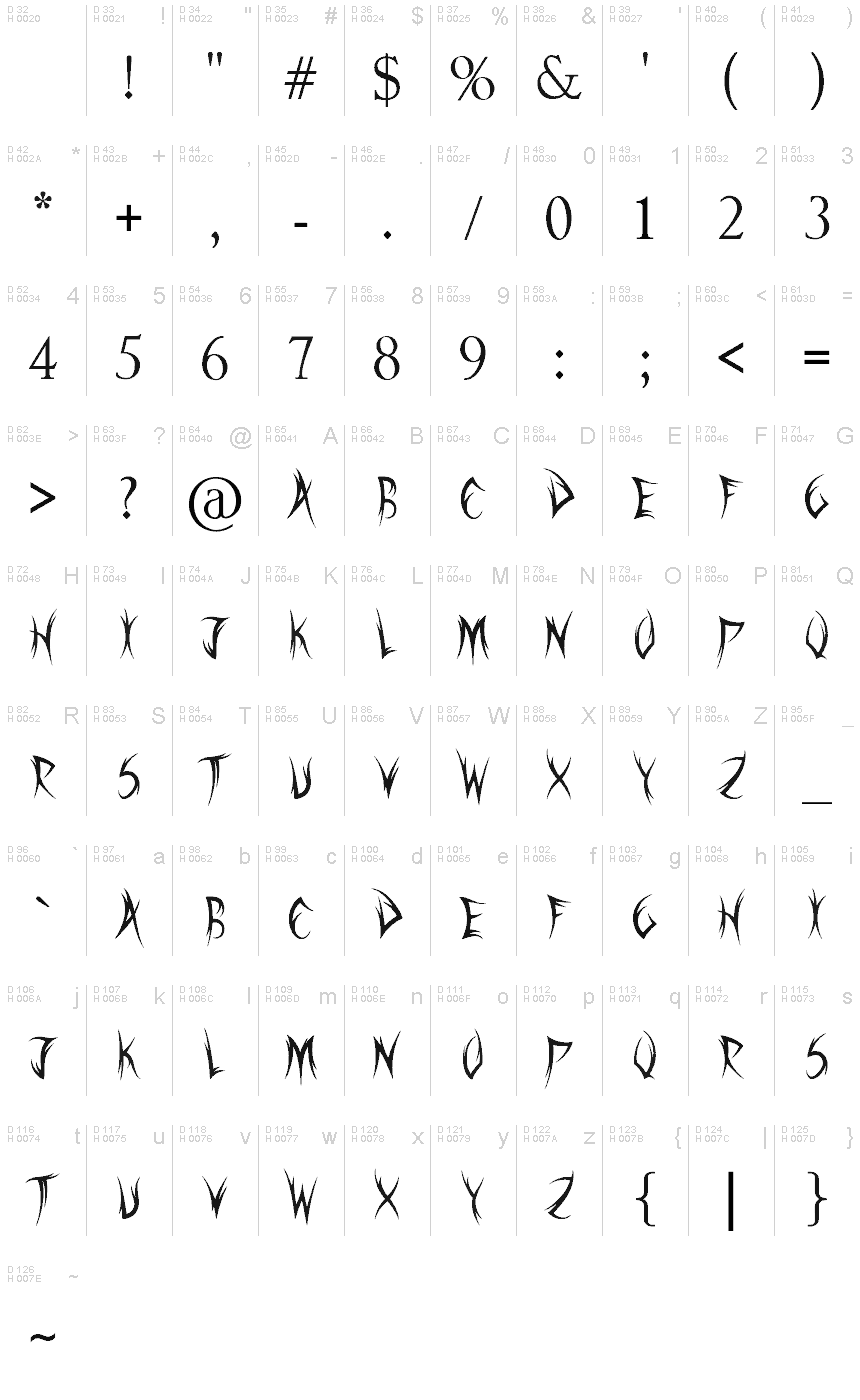
Sword Thrasher, oryginalny projekt od TattooWoo.com, wyróżnia się jako nowoczesna interpretacja klasycznej typografii gotyckiej. Krój ten charakteryzuje się lekką grubością i półwąskim rozstrzeleniem, zapewniając elegancką, a zarazem zdecydowaną obecność na stronie. Ostre krawędzie i płynne krzywizny przywodzą na myśl precyzję ostrza – co jest trafnym nawiązaniem do nazwy.
Estetyka Sword Thrasher polega na unikalnym połączeniu tradycji z nowoczesnym sznytem. Wnosi on aurę współczesnej wyrafinowania, co czyni go idealnym wyborem do projektów wymagających szczypty dramatyzmu bez utraty czytelności. Od brandingu po design wydawniczy, ten krój jest na tyle uniwersalny, by wzbogacić różnorodne kreatywne przedsięwzięcia.
Dzięki nowoczesnemu stylowi i wyrazistemu charakterowi, Sword Thrasher wyróżni się w każdym projekcie, w którym liczy się śmiałość i wyrazistość.
Uwaga: Font zawiera małe litery, cyfry i wszystkie popularne symbole.